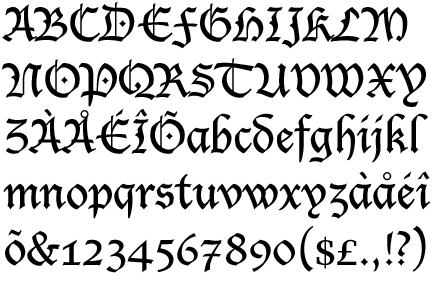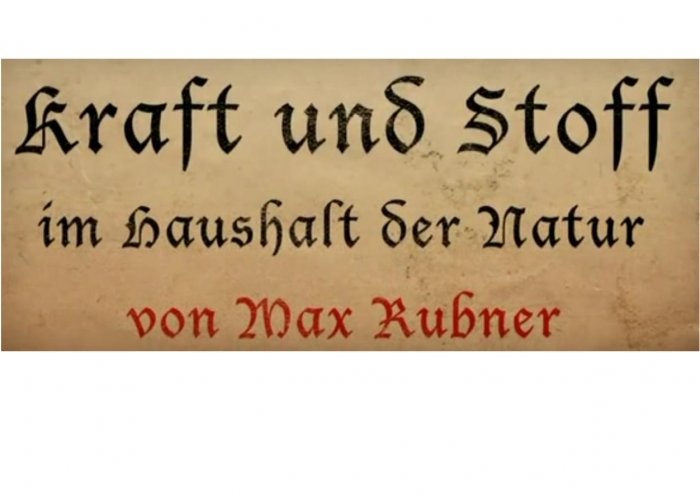
Welche gebrochene Schrift (Leipzig um 1909?) ist das?
ich würde gern wissen, um welche gebrochene Schrift es sich in dem unten stehenden Beispiel handelt. Meine bisherige Recherche im Internet hat mich leider nicht weitergebracht.
Das Buch, dessen Titel zumindest in der fraglichen Schrift gedruckt ist, ist 1909 in Leipzig erschienen - es kann sich hier aber durchaus um eine spätere Auflage handeln.
das Bild zeigt eine Schwabacher sieht für mich nach der Lucida Blackletter aus. Diese ist aber relativ neu, keine gute Schwabacher sondern *hüstel* Dekokackig. Das kleine l ist lausig und es besteht Verwechslungsgefahr mit dem ſ (langen s). Daher würde ich von einem Remake im Vintage-Style ausgehen.
Lucida Blackletter
Designers: Charles Bigelow and Kris Holmes
Year: 1992
Das kleine l ist lausig und es besteht Verwechslungsgefahr mit dem ſ (langen s). Daher würde ich von einem Remake im Vintage-Style ausgehen.
Naja, das kleine l war auch schon 1909 lausig, es sei denn, das Buch handelt wirklich von »Haushaſt«.
In jenem Scan wird der Titel mit einem e im Haushalte geschrieben. Der ursprünglich gesucht scheint mir kein Original zu sein.
Naja, das kleine l war auch schon 1909 lausig, es sei denn, das Buch handelt wirklich von »Haushaſt«.
Nenene! Das iſt die Lucida Blackletter, alſo eine neue Dekokackeſchwabacher von 1992. Ich erinnere mich an eines unſerer erſten Treffen. Das ſtand ſie da und sagte „Heiſ!“ Ich verſtand ſie nicht. Warum ein Binnen-s ſtatt einen Schluss-s? „Heis!“ Aber was ſoll das bedeuten und was hat das mit Deutſchland zu tun?